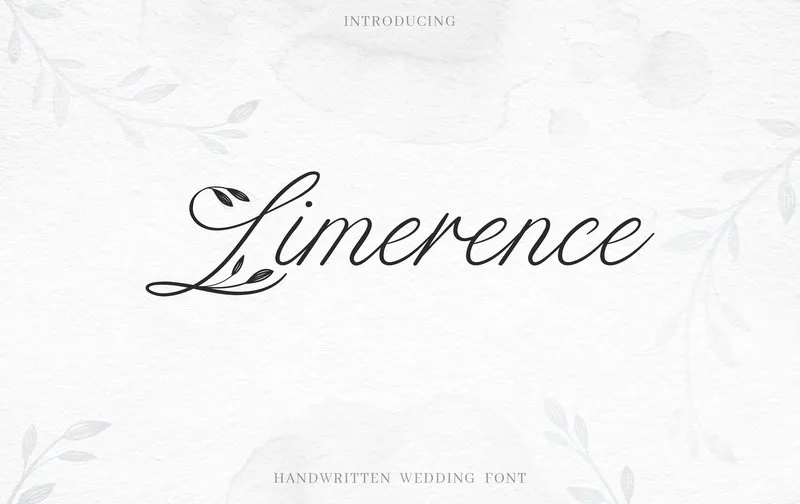
Limerence Script Font – Download Grátis
Introduzimos Limerence. Este é uma fonte premium criada pelo Alphabeta, disponível para download gratuito hoje no Creativemarket. É uma elegante e decorativa font feminina que oferece duas variações: Regular e Thin. Limerence Regular é perfeita para monogramas de casamento e logotipos florais, ideal para inviáveis criativos, embalagens, revistas, lojas florestais, redes sociais, menus de restaurantes, cartões de agradecimento, cabeçalhos e muito mais. O design elegante e delicado da font torna-a perfeita para o universo dos casamentos. Limerence Thin é uma fonte calligráfica que serve igualmente bem em projetos de design de casamento, inviáveis para Instagram, cartas de convite, assinaturas, marcas d’água, logotipos, endereços impressos em letterpress, títulos e até mesmo as celebrações de aniversário. É uma font versátil que está sempre pronta para complementar qualquer design criativo e amoroso.